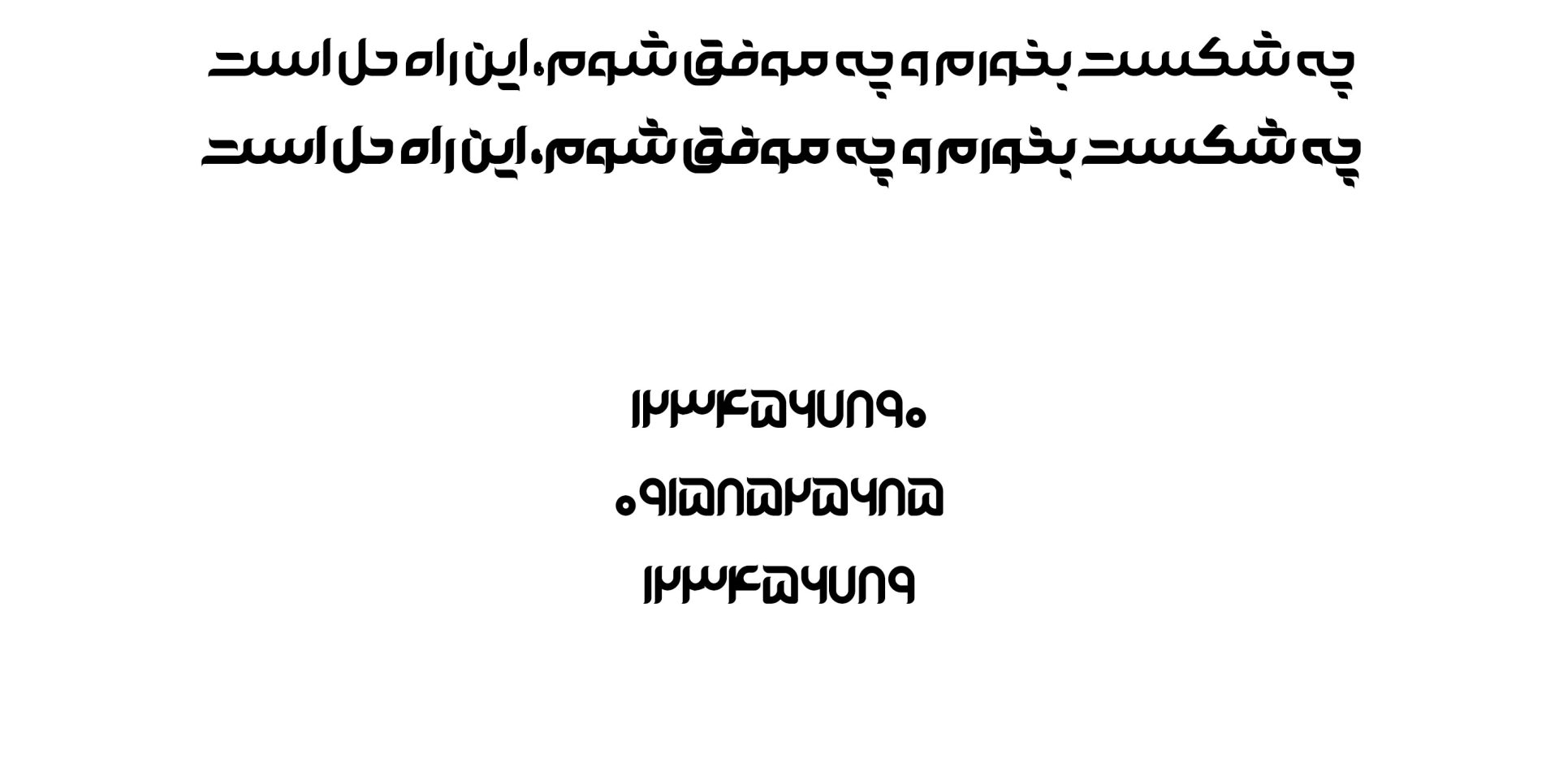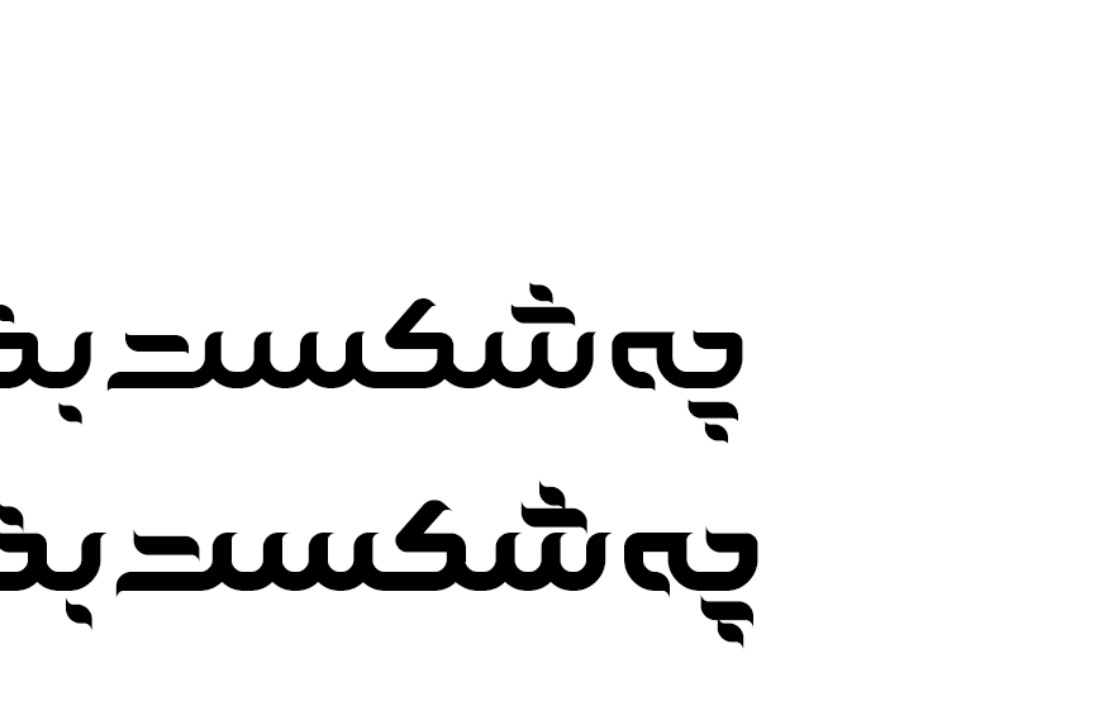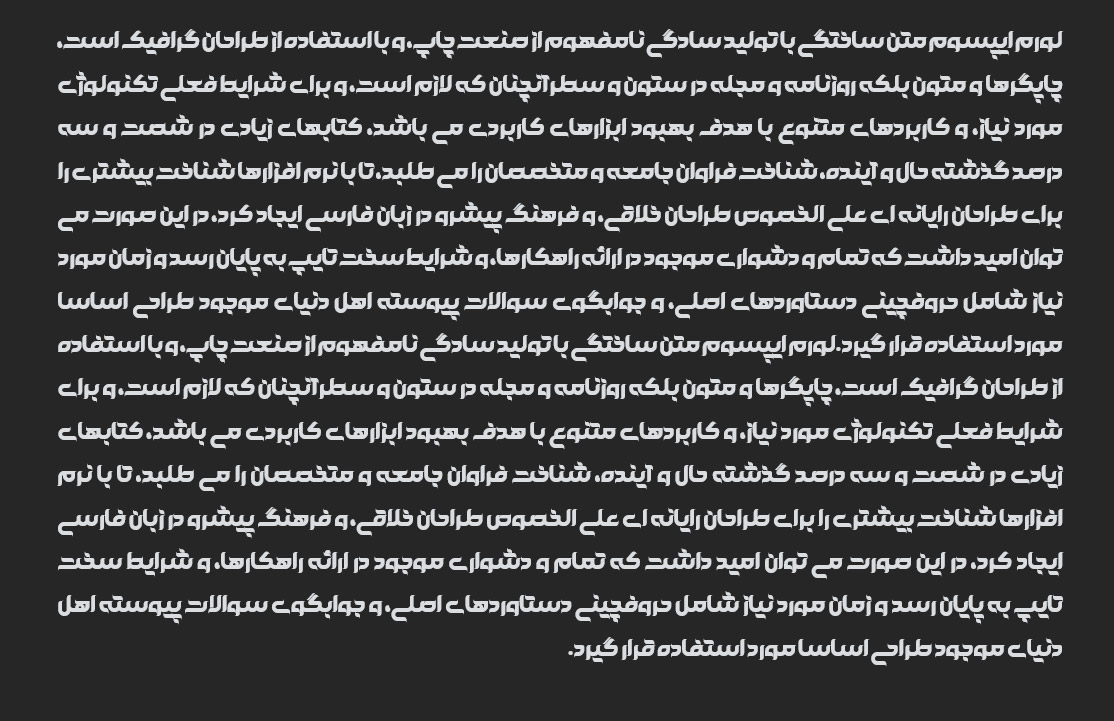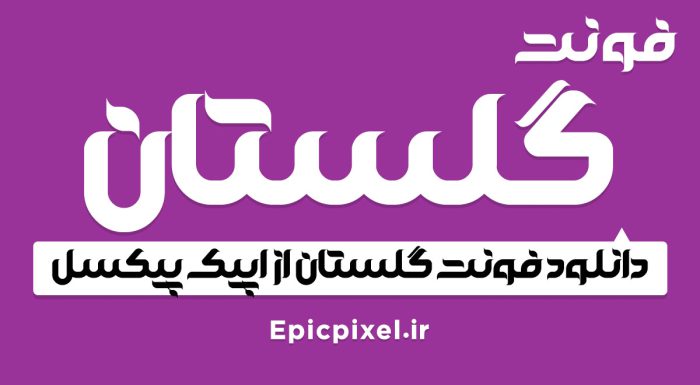
2 فونت گلستان فارسی
فونت گلستان زیبایی و ظرافت در طراحی حروف فارسی
فونت گلستان یکی از فونت های زیبا و ظریف فارسی است که برای طراحی انواع محتواهای چاپی و دیجیتال مناسب است. از ویژگی های اصلی آن می توان به خوانایی عالی، تنوع در سبک ها و همچنین سازگاری با استانداردهای روز دنیا اشاره کرد.
ویژگی های فونت گلستان
فونت گلستان دارای ویژگی های متعددی است که آن را به یکی از فونت های پرکاربرد فارسی تبدیل کرده است. این ویژگی ها عبارتند از:
خوانایی عالی: فونت گلستان دارای تناسب مناسب بین حروف و فضای بین آن ها است که باعث می شود متن نوشته شده با این فونت بسیار خوانا باشد.
تنوع در سبک ها: فونت گلستان در چندین سبک مختلف طراحی شده است که شامل سبک های نازک، نیمه نازک، معمولی، ضخیم و خیلی ضخیم می شود. این تنوع باعث می شود که این فونت برای انواع محتواهای مختلف مناسب باشد.
سازگاری با استانداردهای روز دنیا: فونت گلستان با استانداردهای روز دنیا مانند Unicode و TrueType سازگار است که باعث می شود این فونت در نرم افزارهای مختلف و در سیستم عامل های مختلف قابل استفاده باشد.
موارد استفاده از فونت گلستان
فونت گلستان به دلیل زیبایی و ظرافتی که دارد برای طراحی انواع محتواهای چاپی و دیجیتال مناسب است. از جمله موارد استفاده از این فونت می توان به موارد زیر اشاره کرد:
طراحی پوسترها، کارت ویزیت ها و سایر مواد تبلیغاتی
طراحی کاتالوگ ها، بروشورها و سایر کتاب های چاپی
طراحی تایپوگرافی
نتیجه گیری
فونت گلستان یکی از فونت های زیبا، ظریف و پرکاربرد فارسی است که برای طراحی انواع محتواهای چاپی و دیجیتال مناسب است. اگر به دنبال یک فونت زیبا و با کیفیت برای طراحی محتواهای خود هستید، فونت گلستان یکی از بهترین گزینه های موجود است.
3. آیا فونت گلستان برای طراحی لوگو مناسب است؟
بله، فونت گلستان به دلیل زیبایی و ظرافتی که دارد برای طراحی لوگو مناسب است.
4. آیا فونت گلستان برای طراحی وب سایت مناسب است؟
بله، فونت گلستان به دلیل خوانایی عالی و سازگاری با استانداردهای وب برای طراحی وب سایت مناسب است.